AudiType, Part2_아우디 전용서체의 탄생
볼드 먼데이 폴 반 데 라안과 피터 반 로즈말렌이 디자인한 아우디 전용서체. 1부에서는 이 서체가 어떻게 만들었는지를 다뤘다면 이번 2부에서는 아우디 전용서체의 형태적 특징에 대해 살펴본다. 아우디 전용서체의 디자인 과정을 먼저 알고 싶다면 1부를 먼저 보는 것을 권한다.
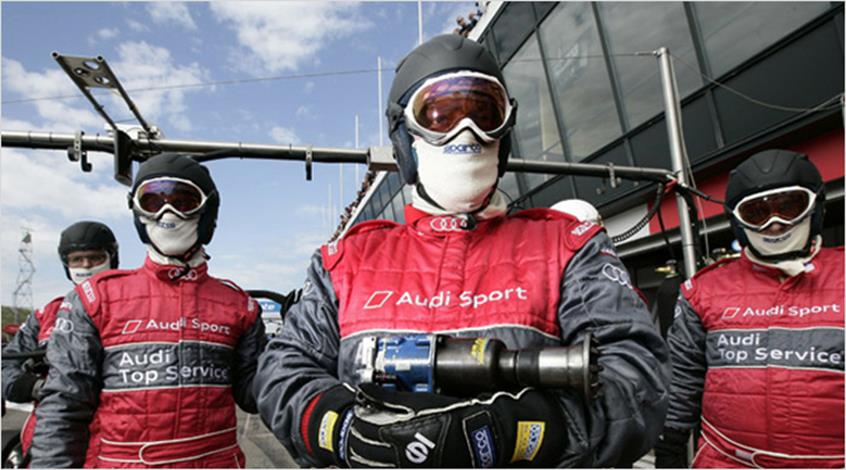
아우디 전용서체(AudiType)는 전혀 새로운 모습으로 나올 것이 기대되었으나, 결과적으로 기존에 아우디가 사용했던 유니버스의 확장 버전인 아우디 산스(Audi Sans)와 많은 구조적 유사점을 지니게 된다. 글자의 비례는 서로 다르지만 두 서체는 동일한 엑스하이트(x-height)와 캡하이트(cap-height)를 가지는 등 일련의 유사성을 가지게 되는데, 이는 전세계적 소통에 있어 급격한 변화보다는 부드러운 과정으로 이행하고자 한 아우디의 의도가 담겨있는 것이다. 폴 반 데 라안과 피터 반 로즈말렌, 두 디자이너 역시 기존 아우디 산스가 가졌던 타이포그래피적 특색에 크게 반하지 않도록 노력했다. 반 데 라안은 ‘아우디 전용서체가 새로 소개되었을 때, 몇몇은 변화된 점을 알아채지 못했다. 이것은 우리의 작업이 의도대로 이루어졌다는 것을 의미한다.’라고 말하기도 했다. 또한 이런 변화로 지역시장의 많은 디자이너들과 에이전시들은 새로운 아우디 전용세체를 받아들이고 적용하는데 큰 어려움이 없었다.
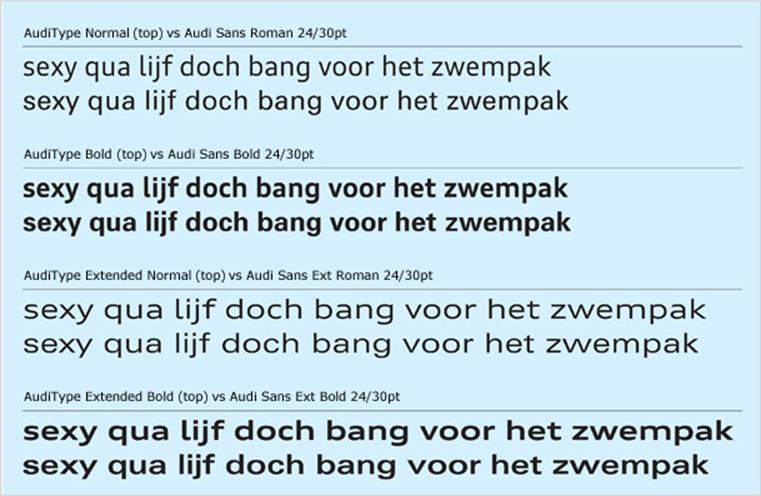
▲ Comparisons of the new AudiType and its predecessor Audi Sans
그렇다고 아우디 전용서체가 나오기까지의 디자인 과정이 쉽게 진행된 것은 아니었다. 이번 프로젝트에는 아우디라는 거대한 브랜드의 개성을 진화시킨다는 막중한 목적과 책임이 있었기에, 서체제작에 있어 상당한 조사와 연구과정을 거쳐야 했다.
Paul van der Laan
‘우리는 첫번째 제안에서 스타일리쉬한 디테일과 미세한 인본주의적 콘크라스트를 가미한 서체를 선보였다. 그러나 이 제안된 서체는 조금은 딱딱하고 억세보인다는 느낌이 들었고, 특별히 느껴지는 매력이 부족해 보였다. 결국 피터와 나는 딱딱한 느낌을 좀 더 부드럽게 누그러뜨려 보기로 했다. 또한 노멀(Normal) 스타일과 익스텐디드(Extended) 스타일 둘 다 유니버스에 비해 약간 좁은 형태를 보여주었던 우리의 제안은 메타디자인과 아우디의 요청에 의해 보다 넓은 비율의 폭으로 수정되었다.’
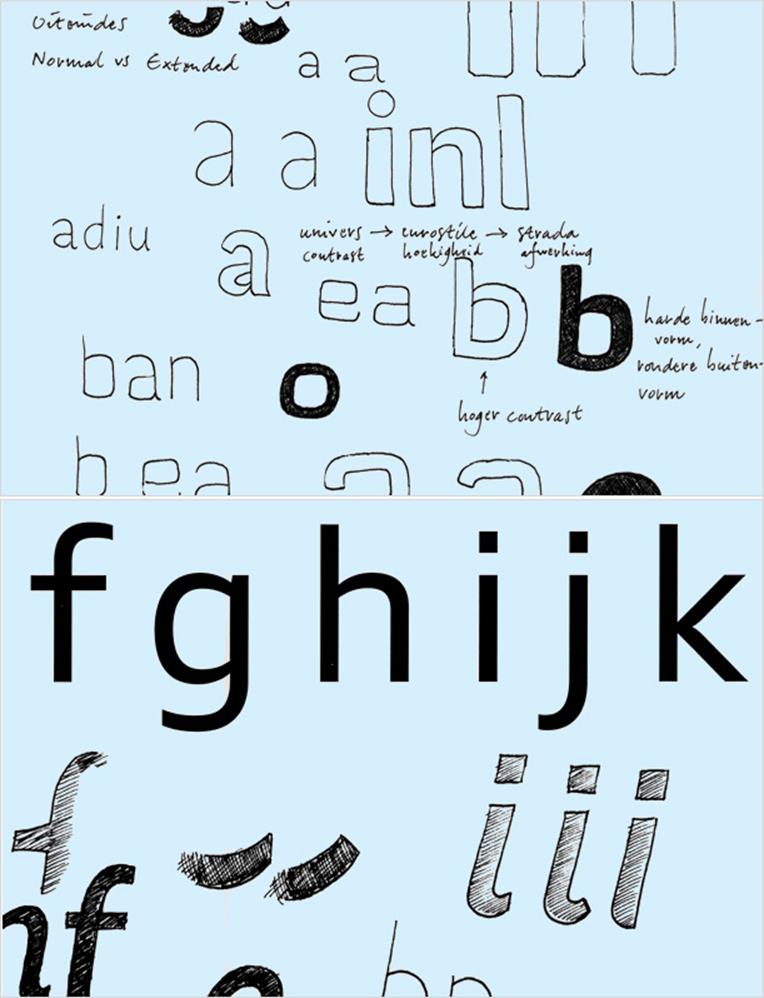
▲ Early sketches for AudiType
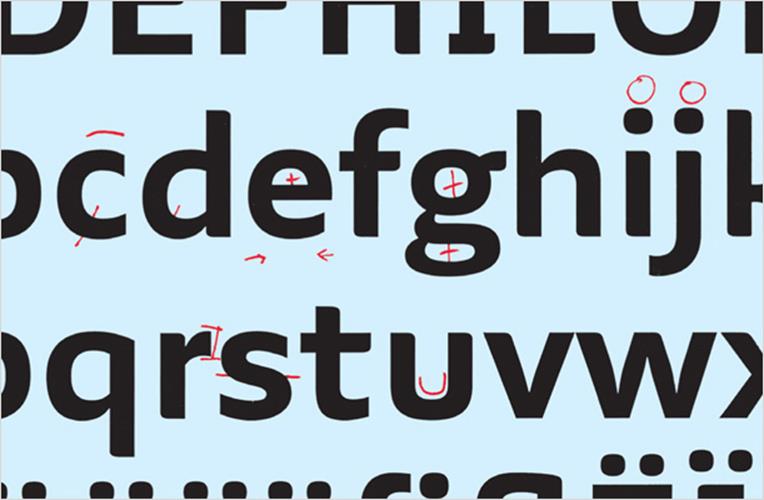
▲ Early notes during the first proposal for AudiType
처음부터 마지막까지 프로젝트가 진행되면서 볼드 먼데이와 메타디자인은 주로 형태적 디테일에 대한 의견 조율에 집중했다. 반 데 라안은 메타디자인과의 작업이 매우 부드러운 분위기에서 이어졌다고 이야기했다. 유일하게 부정적인 피드백을 주었던 것은 아우디 법무팀이였는데, 한가지 에피소드를 얘기하자면 그들은 볼드 먼데이의 첫번째 제안을 단지 섹션사인(§) 때문에 전적으로 거부했다고 한다.
Paul van der Laan
‘아우디 법무팀은 섹션사인(§) 때문에 우리의 제안을 거절했다. 섹션사인처럼 보이지 않는다는 이유 때문이었다. 이에 피터는 이 사인 심볼을 바꾸는데에만 많은 시간을 투자해야만 했다. 그리고 그 형태는 보다 보수적으로 바뀌게 되었다.’
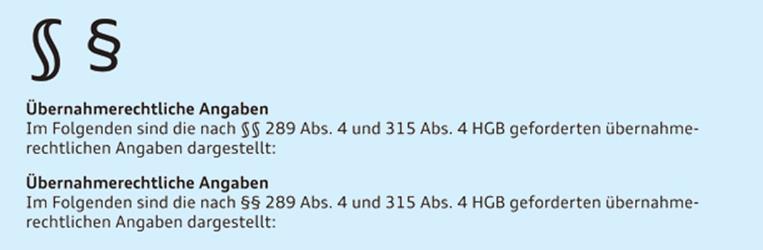
유니버스를 수정해 사용하던 이전 서체에 비해 이번 아우디 전용서체에서 형태적으로 크게 달라진 부분이 하나 있다면, 바로 a,c,e와 같이 터미널(terminal)이 안쪽으로 향한 철자들에서 찾아볼 수 있다. 이전 아우디 산스가 이 철자들에서 닫혀 있는 형태를 보여줬다면, 새로운 전용서체에서는 확연하게 열려있는 모습으로 바뀐 것을 확인 할 수 있다. 이는 의도적으로 디자인의 수평적 긴장감을 더해주기 위함이다.
Van der Laan continues
‘우리는 폭이 좁은 문자들(예를들면 소문자 f, i, t)은 보통보다 넓게, 그리고 넓은 것은 좁게 그려 서체에 보다 테크니컬함이 느껴지도록 했다. 또한 어센더를 스타일별로 길이를 다르게 두었다. 노멀스타일에서는 대문자보다 조금 키가 크다. 이는 본문용으로 쓰일 때나 게르만체 문자(German text)에서는 적절하지만, 익스텐디드 스타일에서는 그렇지 못한 경우가 많다. 때문에 우리는 익스텐디드 스타일에서는 어센더와 대문자의 높이를 같게 맞추었다.’
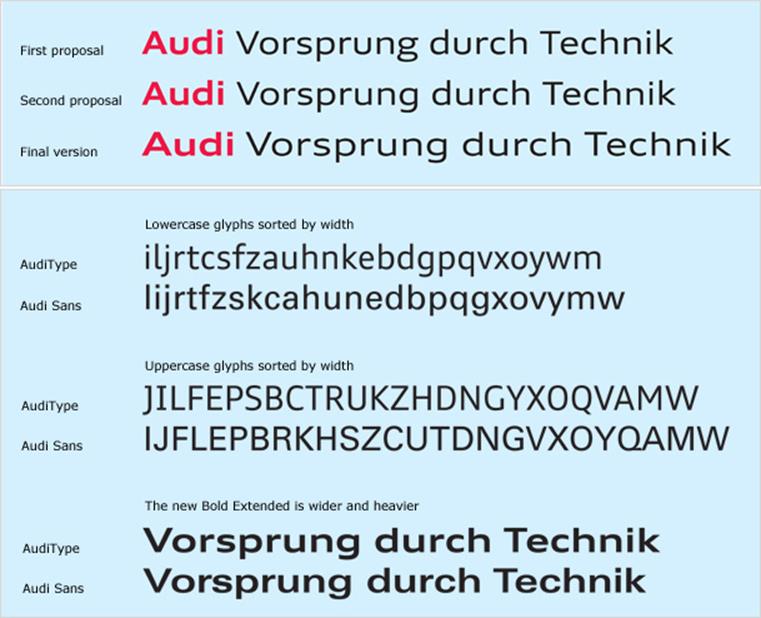
▲ Comparisons of the new AudiType and its predecessor Audi Sans
이번 작업을 되돌아보며 반 데 라안은 메타디자인이 가진 타이포그래피적 날카로운 센스와 프로젝트에 대한 자발적인 열정에 감탄하며, 그들과의 작업에 만족스러움을 표현했다.
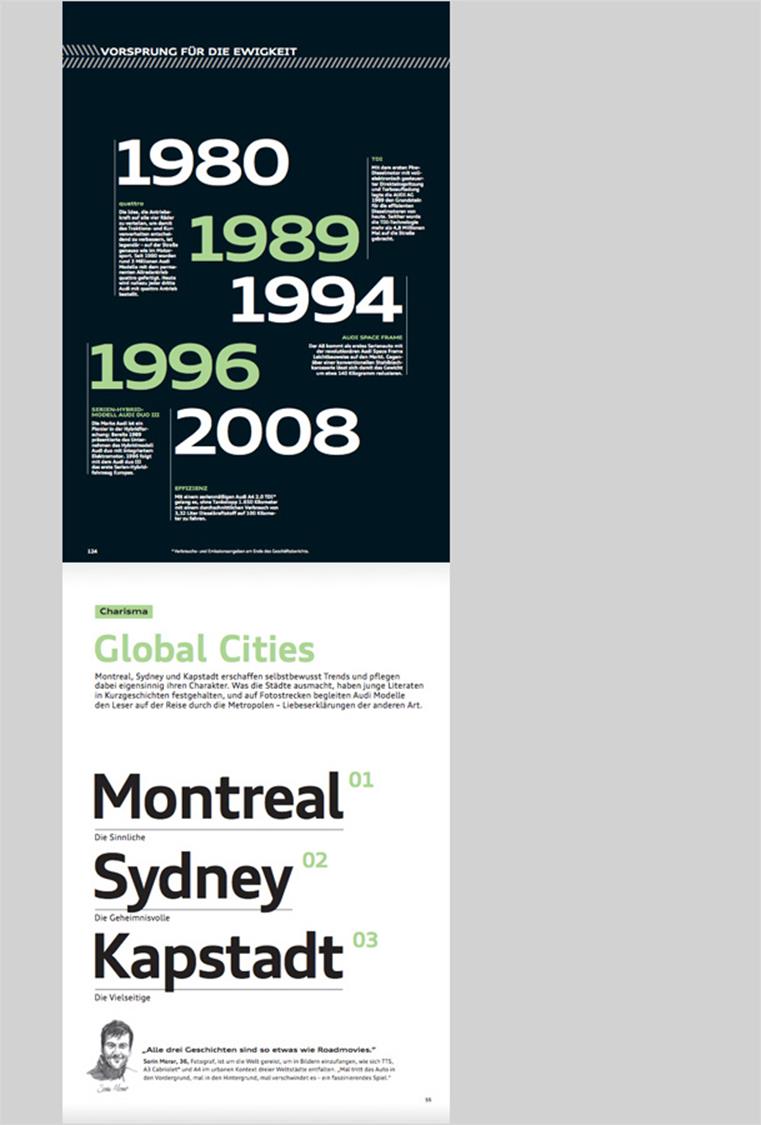
▲ Page from the 2009 Audi Annual Report
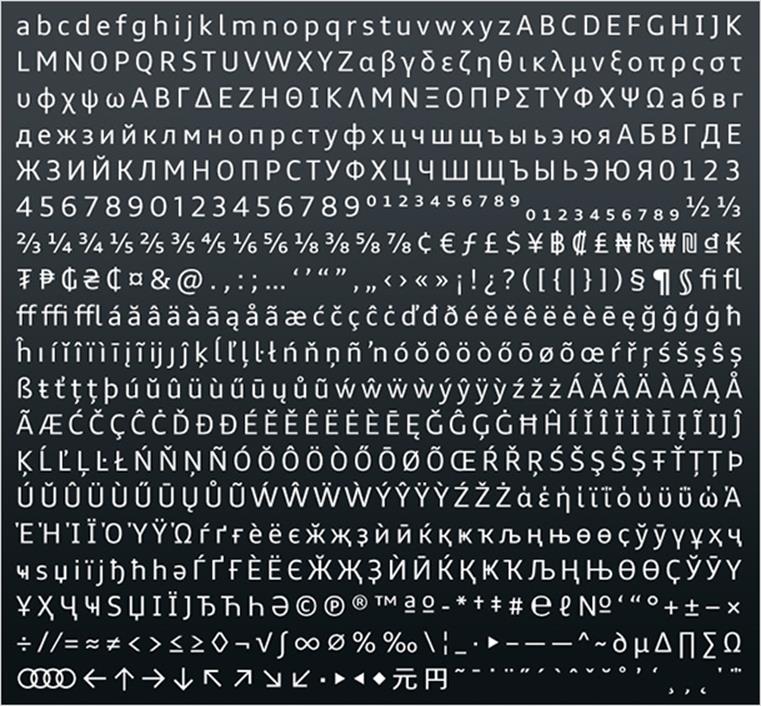
▲ AudiType character set
폴 반 데 라안(Paul van der Laan) 은 서체 & 타이포그래피 디자이너이다. 2003년부터 헤이그에 위치한 로얄 예술 아카데미(Royal Academy of Art) 서체와 미디어(Type & Media) 대학원 과정에서 타입디자인 가르치고 있는 그는 유럽의 많은 학교들과 다양한 국제 컨퍼런스에서 워크숍과 강연활동을 활발히 펼치고 있다. NBCUniversal, Audi AG, Autodesk Inc, Banco Deuno and VPRO와 같은 전세계 클라이언트의 서체를 작업했다.
피터 반 로즈말렌(Pieter van Rosmalen) 은 네덜란드 박스텔 성 루카스(St. Lucas in Boxtel)에서 광고와 그래픽디자인을 공부하고, 로얄 예술 아카데미(Royal Academy of Art) 서체와 미디어(Type & Media) 대학원 과정을 수료했다. NBCUniversal, Audi AG and KPN와 같은 전세계 클라이언트의 작업을 수행했고, 판노(Panno)라는 한국의 거리 표지판 알파벳 표기를 위한 디자인을 하기도 했다.